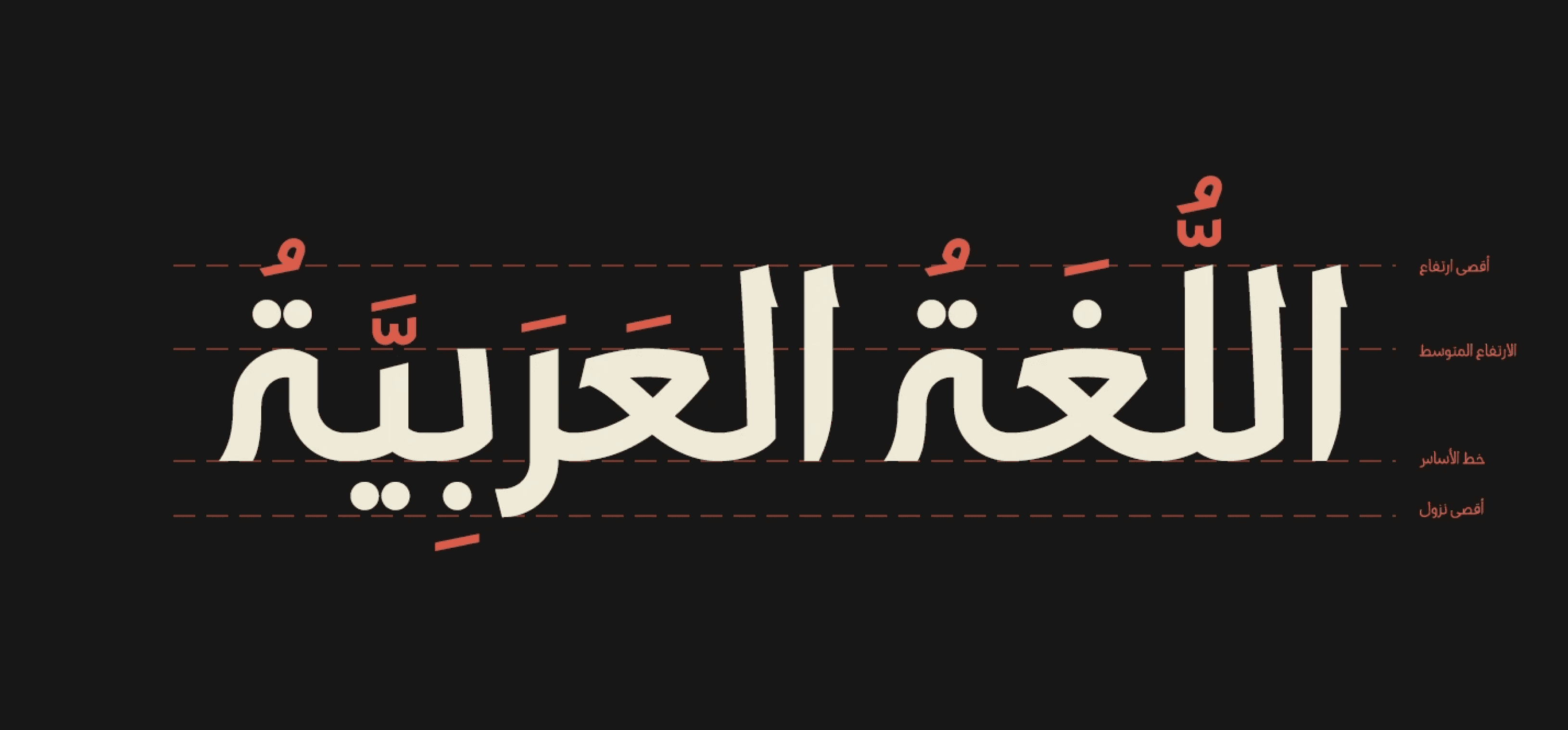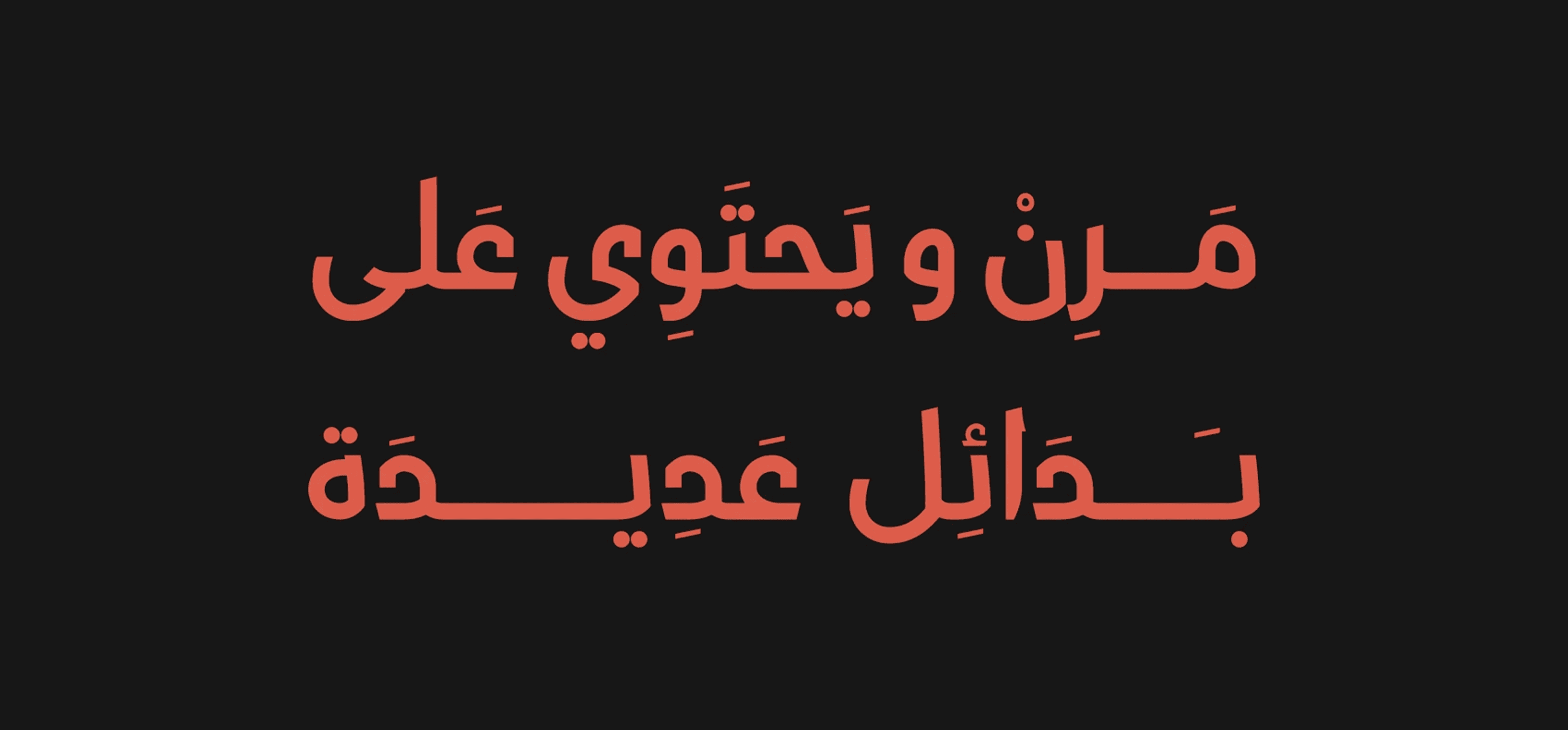
هو خط عصري يستكشف مرونة التباين المستوحاة من الخط العربي الكلاسيكي – الثلث. صُمم خصيصًا ليتناسب مع النصوص القصيرة، العناوين، والاقتباسات.
يأتي Gali بـ 11 وزنًا تبدأ من النحيف (Thin) وصولًا إلى الثقيل (Heavy)، ويحتوي على مجموعة من ميزات OpenType، بالإضافة إلى العديد من البدائل الحرفية والتراكيب الخاصة (Ligatures) التي تدعم العربية، الفارسية، والأردية.
يُعد Gali Modern خيارًا مثاليًا للمصممين الذين يبحثون عن توازن بين الحداثة والطابع الكلاسيكي في الكتابة العربية.